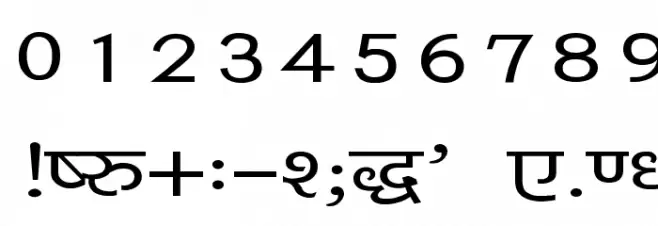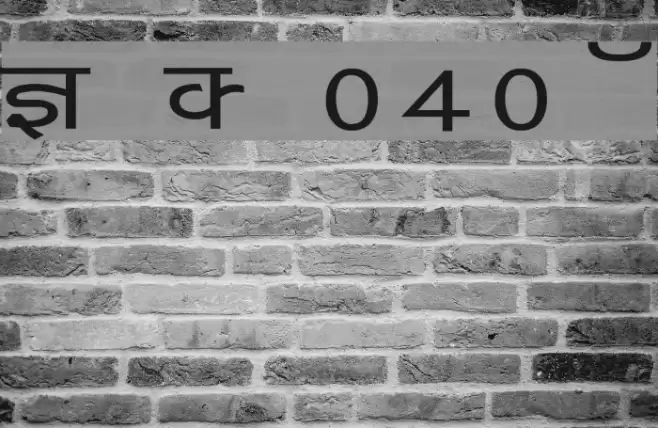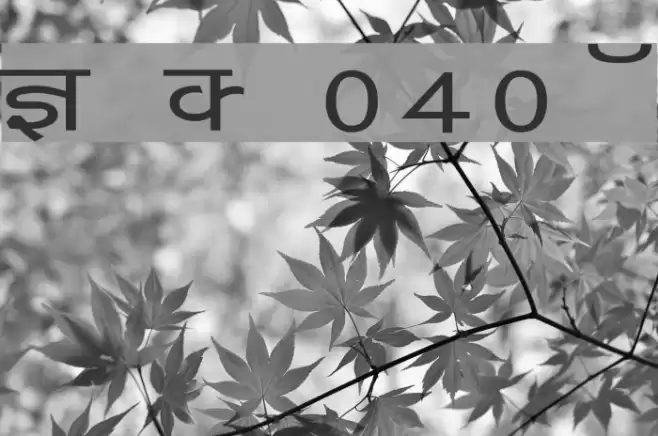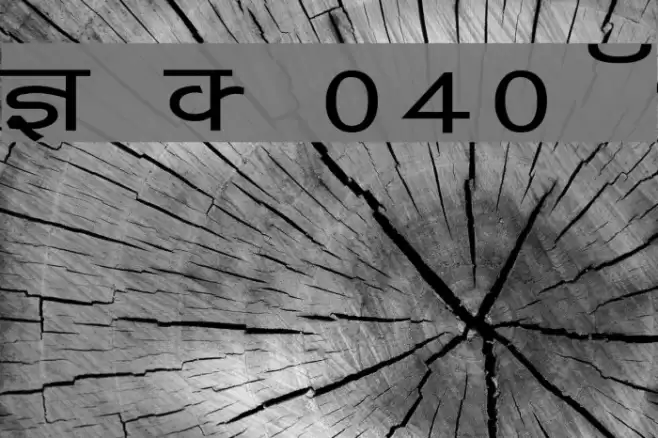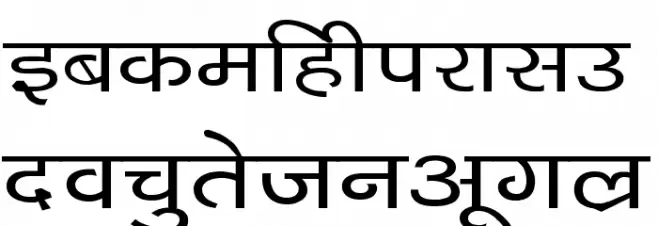
Kruti Dev 040 Wide Font
| चौड़ाई | Expanded |
| उपयोग का मामला | Headlines, Signage, Educational materials |
| सुझाए गए प्रोजेक्ट | Ideal for signage, posters, educational materials, and digital content requiring Devanagari script. |